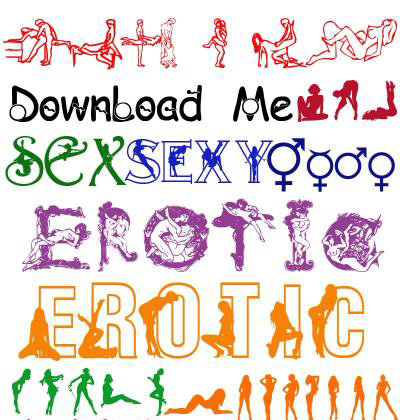
Дополнения Шрифты Татьяна Гапонова 19 февраля 2009 Шрифт - Ero Интересная подборка для людей без предрассудков. Вес - 3.5 MB. Формат - TTF. Скачать Шрифт - Ero
мдааа:(
но думаю будет красиво
5 красивый
для оформления како-нить клуба с данными услугами - самое то!
хахах супер шрифт)
Оригинально!
Кхем.
Я деть. Мне это вредно. Не качаю ==
Пикольный шрифтик >
детям уже все давно известно, а шрифт прикольный))
Великолепный Шрифт
да все!)
Какие то....
Дети уже знают про это давно :Д
Осторожно, тут дети!
так себе, по дилетански
Прикольно, напишу этим шрифтом любимому что-нибудь!
супер но мне ненадо..хотяяяя..................
Мда, шрифт сексуальный.8=)
Прикольна!)))
Вот ЭТО ШРИФТ!!1 вот это то, что надоо)))
забавно)))
Впечатляет...